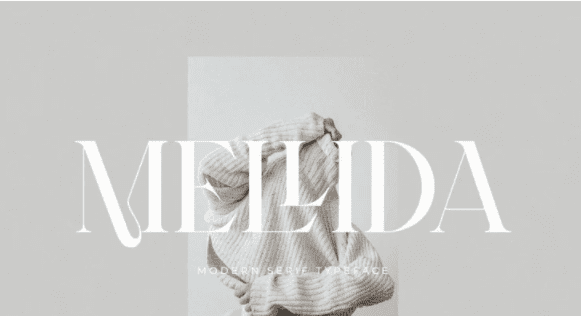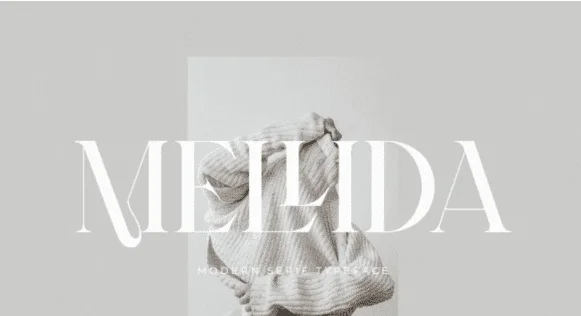
Название: Mellida Font (2022)
Mellida - это современный и элегантный шрифт, который лучше всего использовать для заголовков, логотипов, брендинга, журналов, упаковки продукции и приглашений. Mellida с чистыми линиями и плавными изгибами придает любому проекту дополнительный штрих класса.